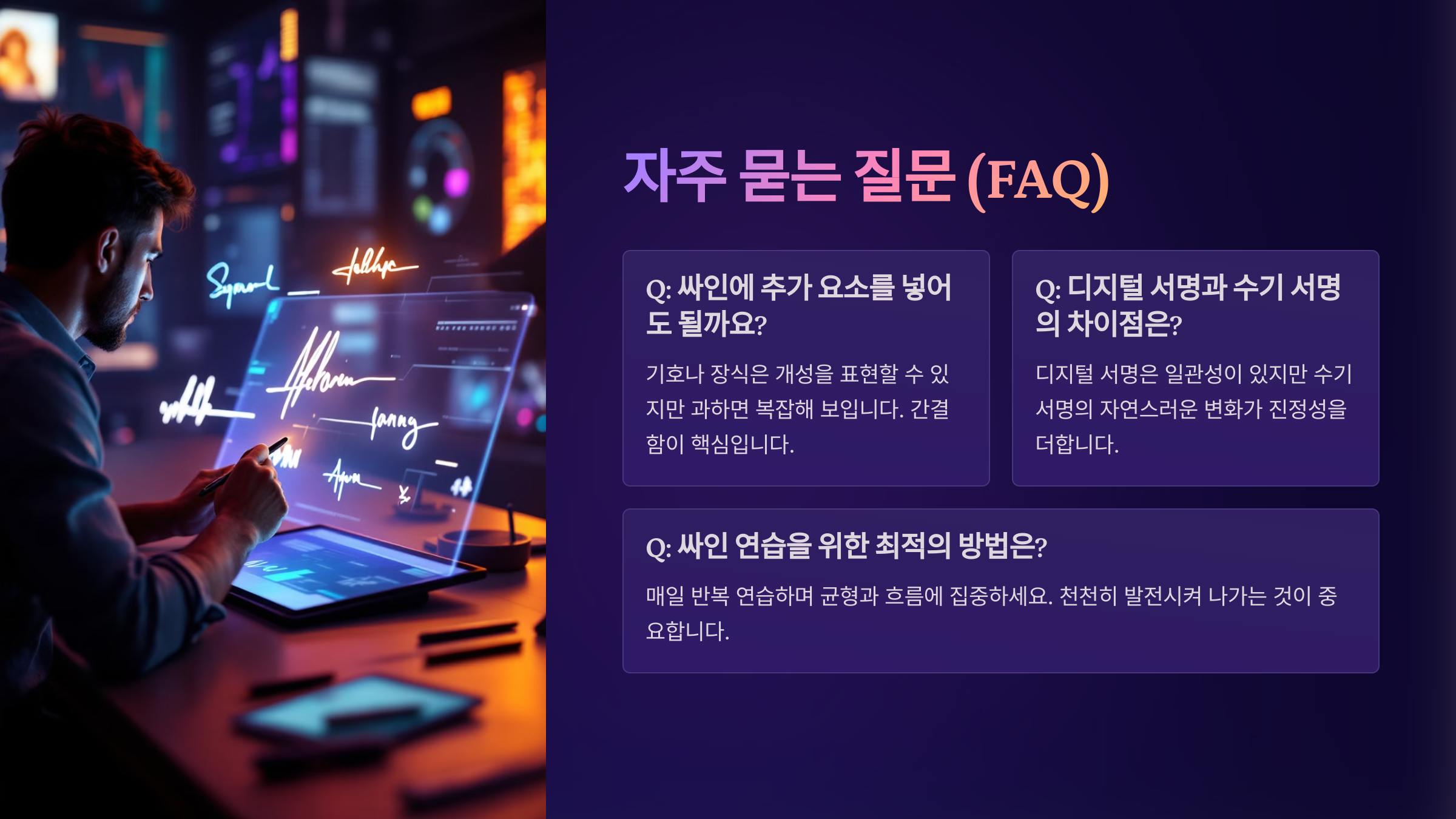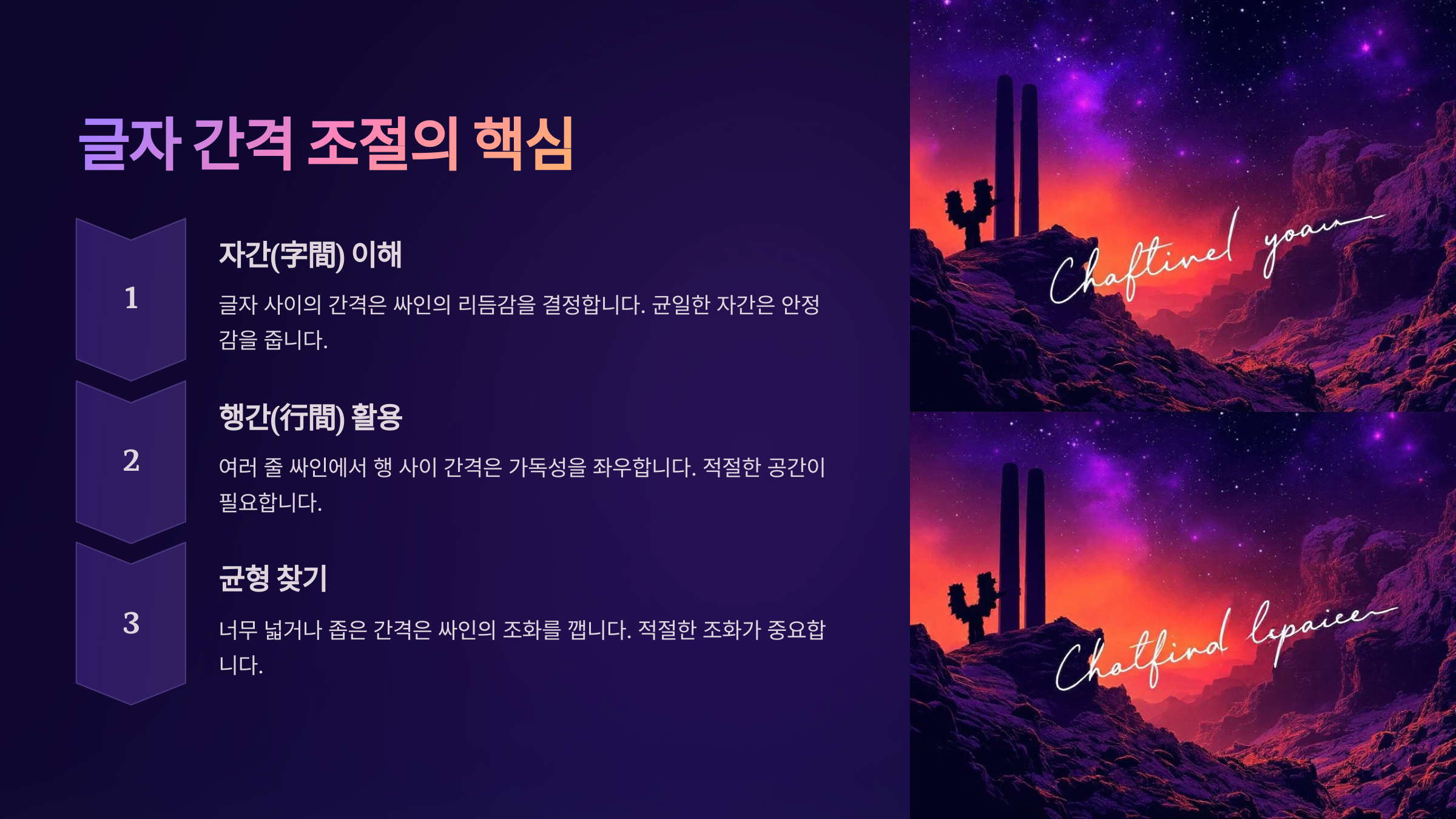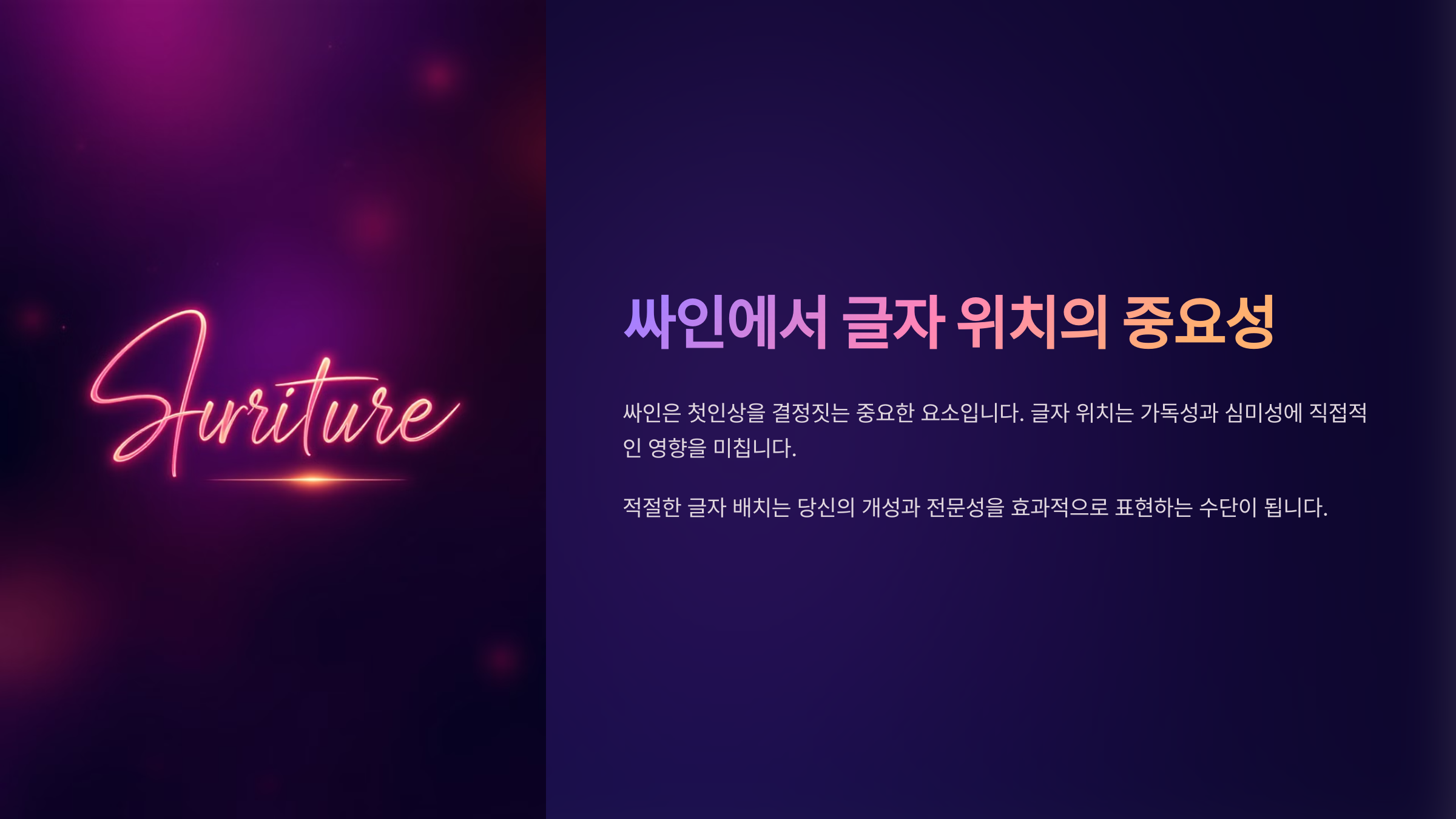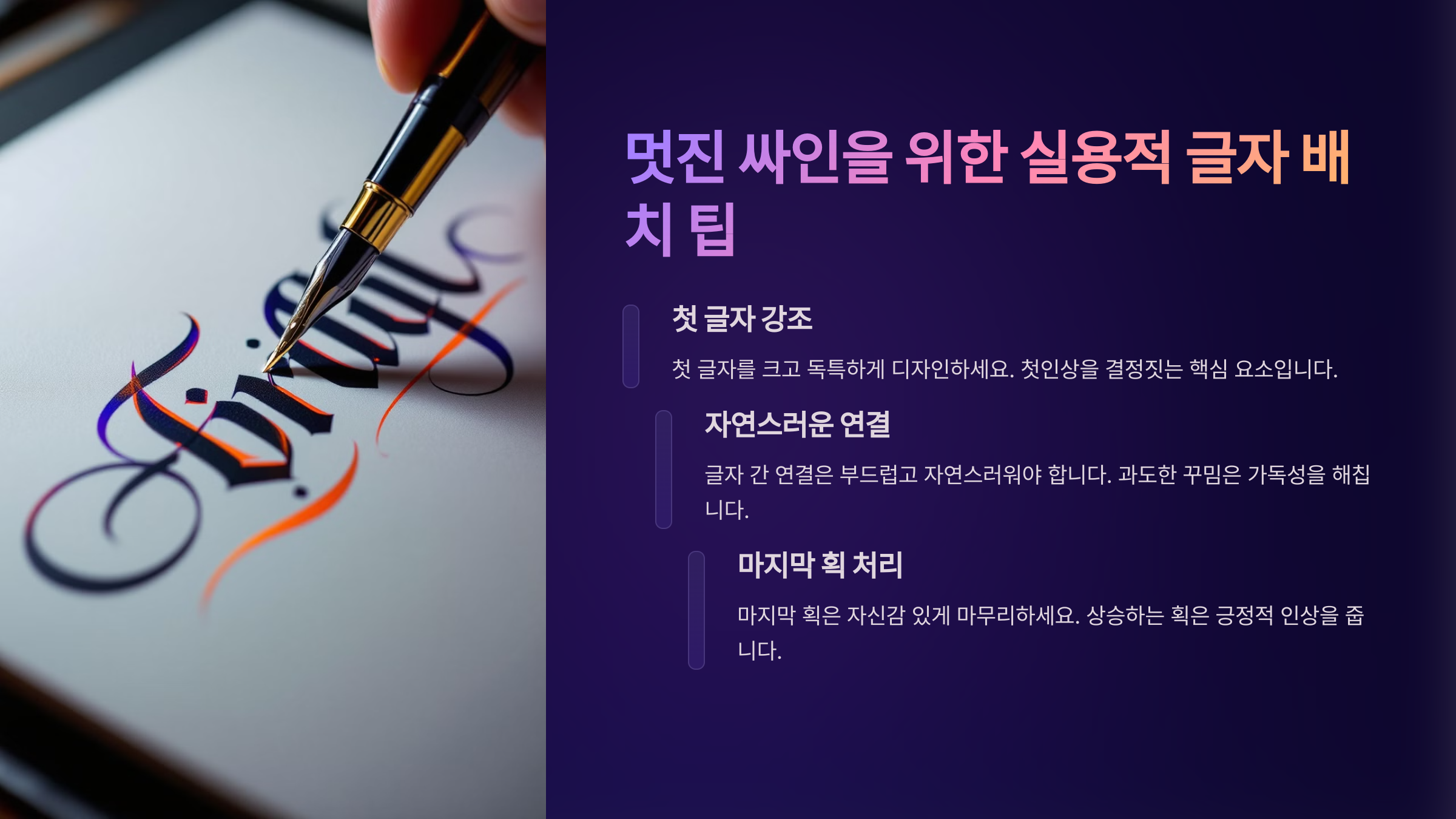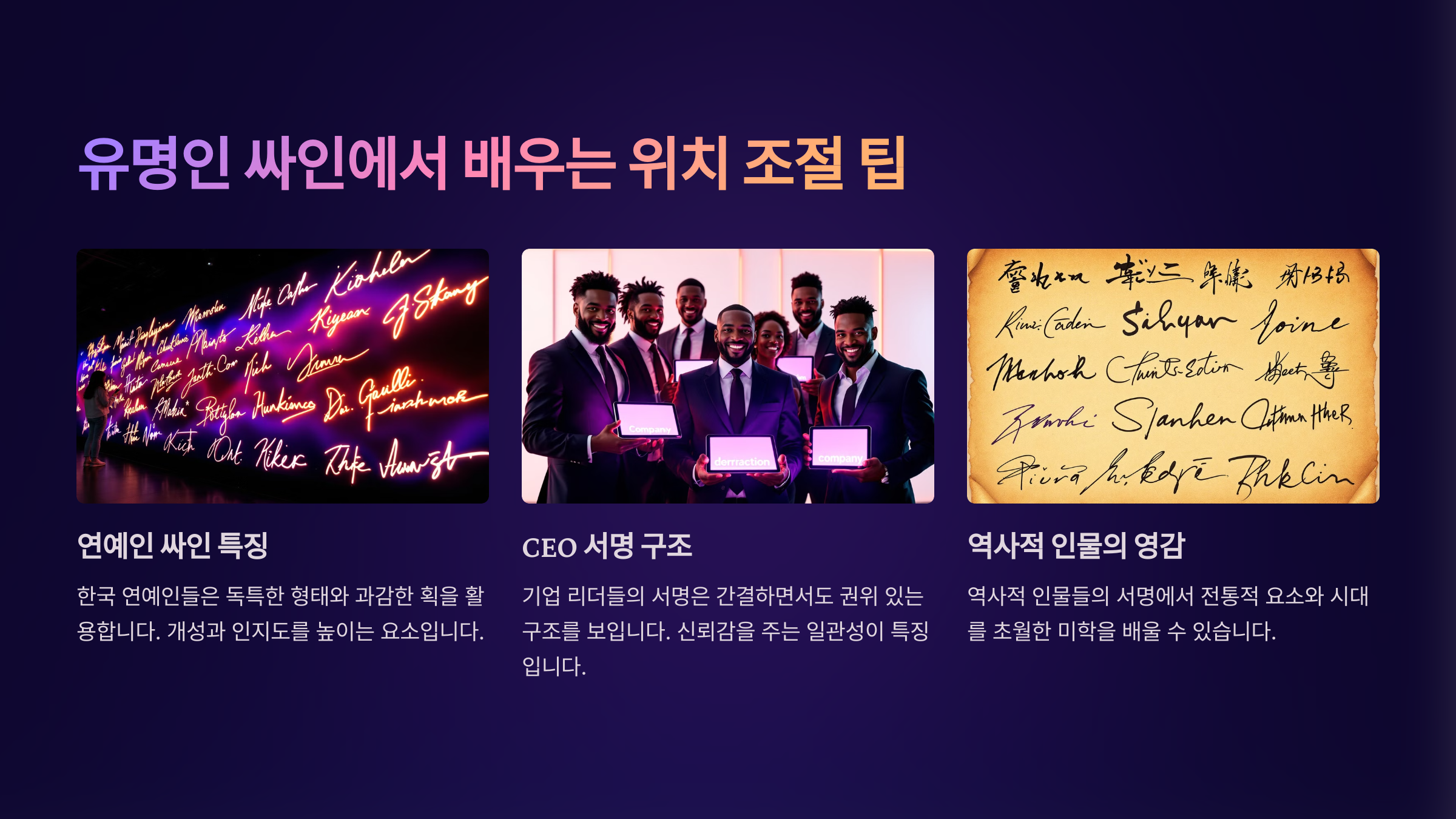
싸인을 만들 때 글자의 위치와 간격을 조절하는 것만으로도 전체적인 느낌이 완전히 달라질 수 있어요. 균형 잡힌 글자 배치는 더 세련되고 전문적인 싸인을 만들어 준답니다! 😎 오늘은 싸인을 더욱 멋지게 보이게 하는 글자의 위치 조절법을 알아볼게요. 🚀
싸인에서 글자 위치가 중요한 이유 ✨
싸인의 디자인은 단순히 글자를 예쁘게 쓰는 것만이 아니라, 어디에 어떻게 배치하느냐에 따라 인상이 크게 달라질 수 있어요. 그렇다면 싸인에서 글자 위치가 중요한 이유는 무엇일까요? 🤔
📌 싸인에서 글자 배치가 중요한 이유
이유 설명
가독성 향상 글자 위치를 정리하면 더 쉽게 읽을 수 있어요.
디자인 완성도 글자의 간격과 정렬을 맞추면 더 깔끔해 보여요.
개성 표현 이니셜을 강조하거나 기울기를 조절하면 나만의 스타일을 만들 수 있어요.
균형 유지 너무 한쪽으로 치우치지 않도록 하면 싸인이 더 조화롭게 보여요.
이제 싸인에서 글자 위치가 중요한 이유를 알았으니, 글자 간격을 조절하는 방법을 배워볼까요? 🤩
글자 간격 조절법 ✍
싸인을 깔끔하고 세련되게 만들려면 글자 간격을 적절하게 조절하는 것이 중요해요. 글자 사이의 간격이 너무 좁으면 답답한 느낌, 너무 넓으면 일관성이 없어 보일 수 있답니다! 🤔
📌 효과적인 글자 간격 조절법
간격 조절 방법 효과
균일한 간격 유지 더 정돈된 느낌을 줄 수 있어요.
이니셜 간격 넓히기 강조하고 싶은 부분이 더 뚜렷해져요.
끝 글자를 길게 빼기 스타일리시하고 독창적인 싸인을 만들 수 있어요.
글자 사이 연결선 추가 유려하고 부드러운 흐름을 줄 수 있어요.
글자 간격만 조금 조절해도 더 세련된 싸인이 될 수 있어요! 그럼 싸인의 정렬과 배치 방법은 어떻게 하면 좋을까요? 😊
글자의 정렬과 배치 방법 📏
싸인을 만들 때 글자의 위치를 잘 정리하면 더 균형 잡히고 세련된 느낌을 줄 수 있어요! 글자의 정렬 방식에 따라 전혀 다른 분위기를 연출할 수 있답니다. 🤩
📌 싸인 정렬 방식에 따른 느낌
• 📍 왼쪽 정렬 → 단정하고 정돈된 느낌
• 📍 중앙 정렬 → 균형 잡힌 안정적인 느낌
• 📍 기울어진 정렬 → 역동적이고 활동적인 인상
• 📍 곡선형 배치 → 감성적이고 부드러운 스타일
이제 글자 정렬법도 알았으니, 균형 잡힌 싸인을 만들기 위한 방법도 살펴볼까요? 😊
균형 잡힌 싸인 디자인 ⚖
싸인을 디자인할 때 균형을 맞추는 것이 중요해요. 글자 위치가 한쪽으로 치우치거나 불균형하면 어수선한 느낌을 줄 수 있어요. 그럼 어떻게 하면 싸인을 더 조화롭고 세련되게 만들 수 있을까요? 🤔
📌 균형 잡힌 싸인을 위한 3가지 원칙
• ✔ 좌우 균형 유지 → 글자가 한쪽으로 치우치지 않도록 조정하세요.
• ✔ 크기 대비 맞추기 → 이니셜이 너무 크거나 작지 않도록 조절하세요.
• ✔ 마무리 요소 활용 → 밑줄(__), 점(•), 별(⭐) 등을 추가하면 안정감이 생겨요.
균형을 맞춘 싸인은 더 깔끔하고 세련된 느낌을 줄 수 있어요! 그럼 실제로 유명인의 싸인을 살펴보면서 더 많은 인사이트를 얻어볼까요? 🔍
유명인의 싸인에서 배우는 위치 조절 🌟
많은 유명인들은 싸인을 통해 자신만의 개성을 표현하고 있어요. 그들의 싸인을 보면 글자 배치와 균형을 맞추는 방법을 배울 수 있답니다. ✍
📌 유명인의 싸인 스타일 분석
유명인 싸인 스타일 특징
스티브 잡스 단순한 필기체 미니멀하면서도 현대적인 균형
마이클 잭슨 곡선이 많은 스타일 예술적이고 감성적인 분위기
일론 머스크 강한 직선형 디자인 자신감 있고 강한 인상
도널드 트럼프 각지고 직선적인 배치 권위적이고 강한 느낌
이처럼 싸인의 글자 위치와 배치만 바꿔도 완전히 다른 인상을 줄 수 있어요! 그럼 마지막으로 더 멋진 싸인을 만들기 위한 실전 팁을 알아볼까요? 😉
멋진 싸인을 위한 글자 배치 팁 🎨
싸인의 인상을 좌우하는 가장 중요한 요소 중 하나는 글자의 배치와 균형이에요. 조금만 신경 써서 위치를 조절하면 더 세련되고 멋진 싸인을 완성할 수 있어요! ✍
✅ 글자 배치를 조절하는 3가지 핵심 팁
• ✔ 이니셜을 강조하라 → 이름의 첫 글자를 더 크게 써서 포인트를 줄 수 있어요.
• ✔ 마지막 획을 활용하라 → 싸인의 끝부분을 길게 빼거나 곡선을 추가하면 더 감각적이에요.
• ✔ 공간을 전략적으로 사용하라 → 글자들이 너무 붙거나 떨어지지 않도록 적절한 간격을 유지하세요.
이제 글자 배치의 기본 원칙을 알았으니, 마지막으로 싸인 디자인과 관련된 자주 묻는 질문(FAQ)을 살펴볼까요? 🤩
FAQ ❓
Q1. 싸인에서 글자 배치를 조절하면 어떤 효과가 있나요?
A1. 글자의 위치를 조절하면 싸인의 가독성을 높이고, 세련된 느낌을 더할 수 있어요. 균형이 맞춰진 싸인은 더 정돈된 인상을 줄 수 있어요! 😆
Q2. 싸인에서 가장 중요한 글자는 어떤 글자인가요?
A2. 보통 이름의 첫 글자(이니셜)가 가장 중요해요! 첫 글자를 강조하면 더 인상적인 싸인을 만들 수 있답니다. ✨
Q3. 싸인에서 글자를 기울이면 어떤 효과가 있나요?
A3. 글자를 기울이면 역동적이고 활동적인 느낌을 줄 수 있어요. 반대로 수직 정렬하면 더 안정적이고 신뢰감 있는 인상을 줄 수 있어요. 🔥
Q4. 싸인의 글자 크기를 조절하는 방법이 있나요?
A4. 네! 이니셜을 더 크게 강조하고, 나머지 글자는 상대적으로 작게 조절하면 더욱 전문적이고 세련된 느낌을 줄 수 있어요. 📏
Q5. 싸인을 만들 때 글자를 너무 붙이면 안 좋은가요?
A5. 너무 붙이면 읽기 어렵고 답답한 인상을 줄 수 있어요. 적절한 공간을 두고 배치하면 더 자연스럽고 가독성이 좋아집니다. 😉
Q6. 싸인에서 밑줄(—)이나 점(•)을 활용하는 방법이 있나요?
A6. 네! 밑줄(—)은 싸인의 마무리를 강조할 때 좋고, 점(•)은 세련된 마무리 효과를 줄 수 있어요! ✍
Q7. 싸인을 더 감각적으로 만들기 위한 아이디어가 있을까요?
A7. 물론이죠! 싸인을 감각적으로 만들려면 ✅ 이니셜을 변형해서 독창적인 디자인을 만들어보세요. ✅ 마지막 획을 강조해서 스타일리시한 마무리를 해보세요. ✅ 곡선을 활용해 부드럽고 세련된 느낌을 연출해 보세요. 🎨
Q8. 싸인의 글자 위치를 쉽게 조절하는 연습 방법이 있을까요?
A8. 네! 격자 노트를 활용해서 싸인을 연습하면 더 정확하게 글자의 크기와 위치를 조절할 수 있어요. 📝
싸인의 글자 위치를 조절하는 것만으로도 완전히 새로운 느낌의 디자인을 만들 수 있어요! ✔ 균형 잡힌 배치 ✔ 적절한 간격 유지 ✔ 이니셜과 마무리 강조 이 세 가지를 기억하면서 더 멋진 싸인을 완성해보세요! 🚀